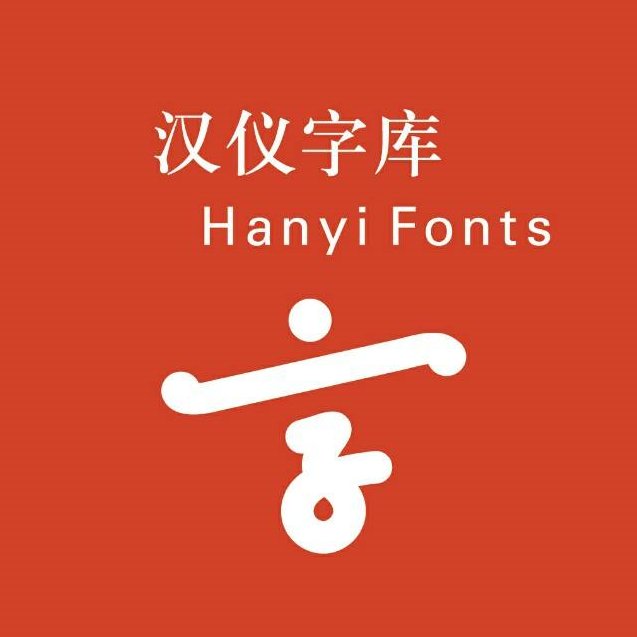
据悉,近日北京汉仪创新科技股份有限公司(原名北京汉仪科印信息技术有限公司)拟在创业板上市,近日已就上市辅导情况向北京证监局进行备案,汉仪成立于1993年。汉仪上市 | 汉仪字库上市那就成为中国字体字库第一家上市的企业。
发展历程:
北京汉仪创新科技股份有限公司(原名北京汉仪科印信息技术有限公司)成立于1993年,是中国大陆最早专业从事字形设计、字库产品开发、汉字信息技术研究、汉字应用解决方案的,拥有核心自主知识产权的文化创意与高新技术企业。
2011年以来,汉仪公司一直承担着被列入《国家"十一五"时期文化发展规划纲要》的重大建设项目,93年成立至今,汉仪已经向国内外市场推出300余款中文字库。
秉承着传统字库行业的工匠精神,汉仪字库复刻的清代扬州雕版印刷极盛时期标志的康熙版《全唐诗》雕版字体,与黑体大家齐立老师倾力设计的字库产品汉仪旗黑,以及同期创作的元隆黑、铁线黑、新人文宋、小麦体等大量优秀字库作品皆活跃于一线应用市场,受到行业内外的一致好评。